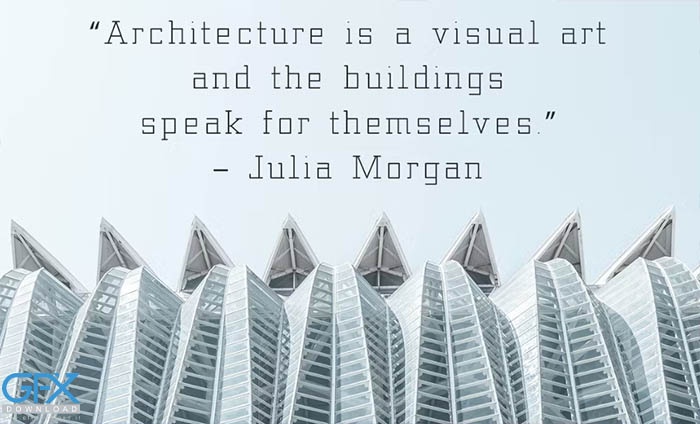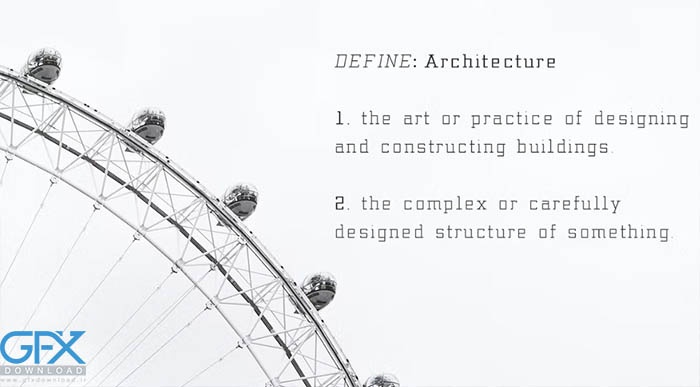
Architect یک فونت دیجیتال سرگرم کننده است که از دوران اولیه رایانه های شخصی الهام گرفته شده است. این فونت برای سرفصلها، لوگوها، طرحبندیها و محتوای تاثیرگذار عالی است. دانلود فونت معماری Architect به زیبایی با بسیاری از فونت ها سازگار می شود و ممکن است با هر پروژه ای که روی آن کار می کنید به خوبی کار کند.